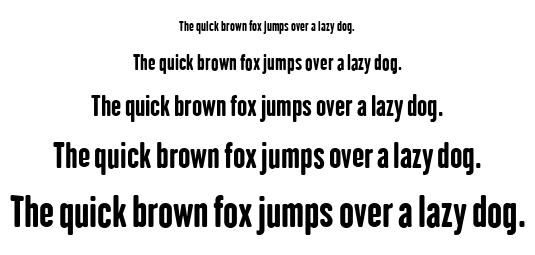
Tipografía sans-serif, black y extra condensada, con acabados redondeados en los vértices. Perfecta para diseñar posters y grandes titulares donde se busque una fuente con fuerza y económica para el espacio horizontal.